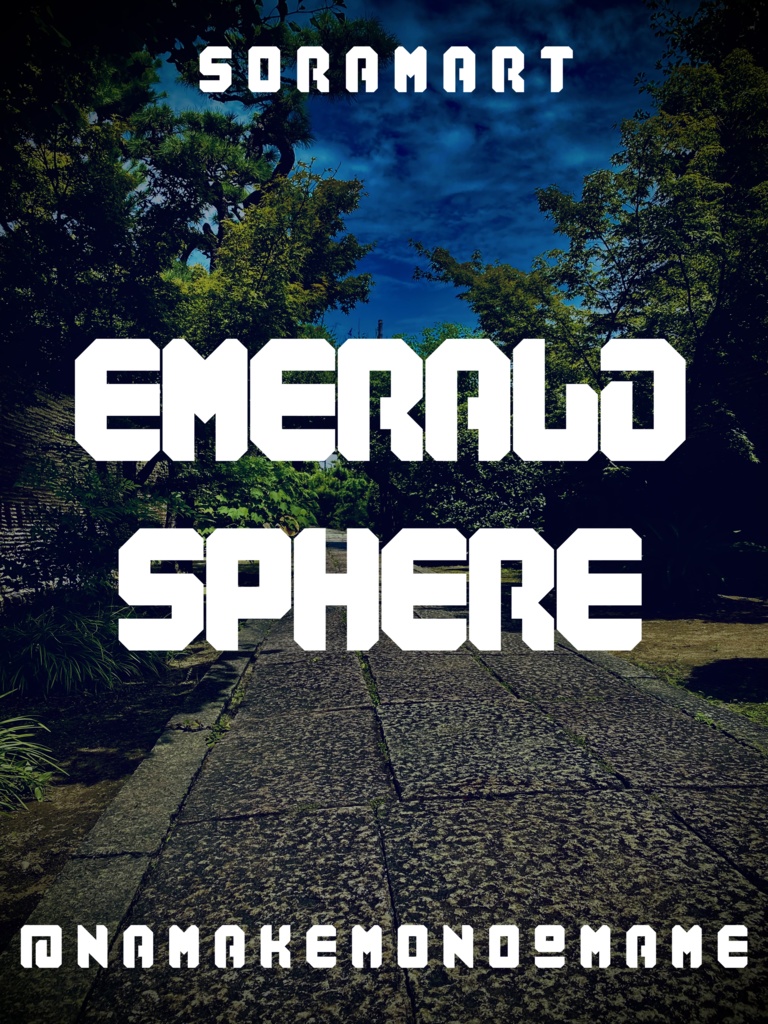
そらマートフォントデータ”Emerald Sphere”Digital2,500 JPYAdd to CartBuy a GiftAbout Gift八角形シルエットのポップ調フォント "Emerald Sphere" です。 「TrueTypeフォントファイル」という形式です。 ダウンロードした後、Zipファイル内のデータをインストールしてお使いください。 このフォントは商用利用可となっております。 お客様の制作・創作活動のお役に立てれば幸いです。 ※使用上の注意事項などは、添付のReadmeをお読みください。そらマートVisit FANBOX!Fontsフォントデータ”Star Shoot Black”そらマート0 JPYFontsフォントデータ”Mars Invader Balloon”そらマート2,500 JPYFontsフォントデータ”Mars Invader Wide”そらマート0 JPYFontsフォントデータ”Mars Invader”そらマート0 JPYFontsフォントデータ”Rock Cut Serif”そらマート2,500 JPYFontsフォントデータ”Rock Cut Drop Wide”そらマート2,500 JPYFontsフォントデータ”Rock Cut Drop”そらマート2,500 JPYFontsフォントデータ”Longtail Sans Serif Slashed”そらマート2,500 JPYFontsフォントデータ”Longtail Sans Serif Bold”そらマート2,500 JPYFontsフォントデータ”Longtail Sans Serif”そらマート2,500 JPYFontsフォントデータ”Pretty Commando”そらマート2,500 JPYFontsフォントデータ”Abyss Dive Punk Retro”そらマート2,500 JPYFontsフォントデータ”Abyss Dive Punk Wide”そらマート2,500 JPYFontsフォントデータ”Abyss Dive Punk”そらマート2,500 JPYFontsフォントデータ”Emerald Sphere Sprite”そらマート2,500 JPYFontsフォントデータ”Emerald Sphere Long”そらマート2,500 JPYFontsフォントデータ”Monolith Glitch”そらマート2,500 JPYFontsフォントデータ”Monolith Formula”そらマート2,500 JPYFontsフォントデータ”Rolling Cute”そらマート2,500 JPYFontsフォントデータ”Tricky Wire Merge”そらマート2,500 JPYSee More